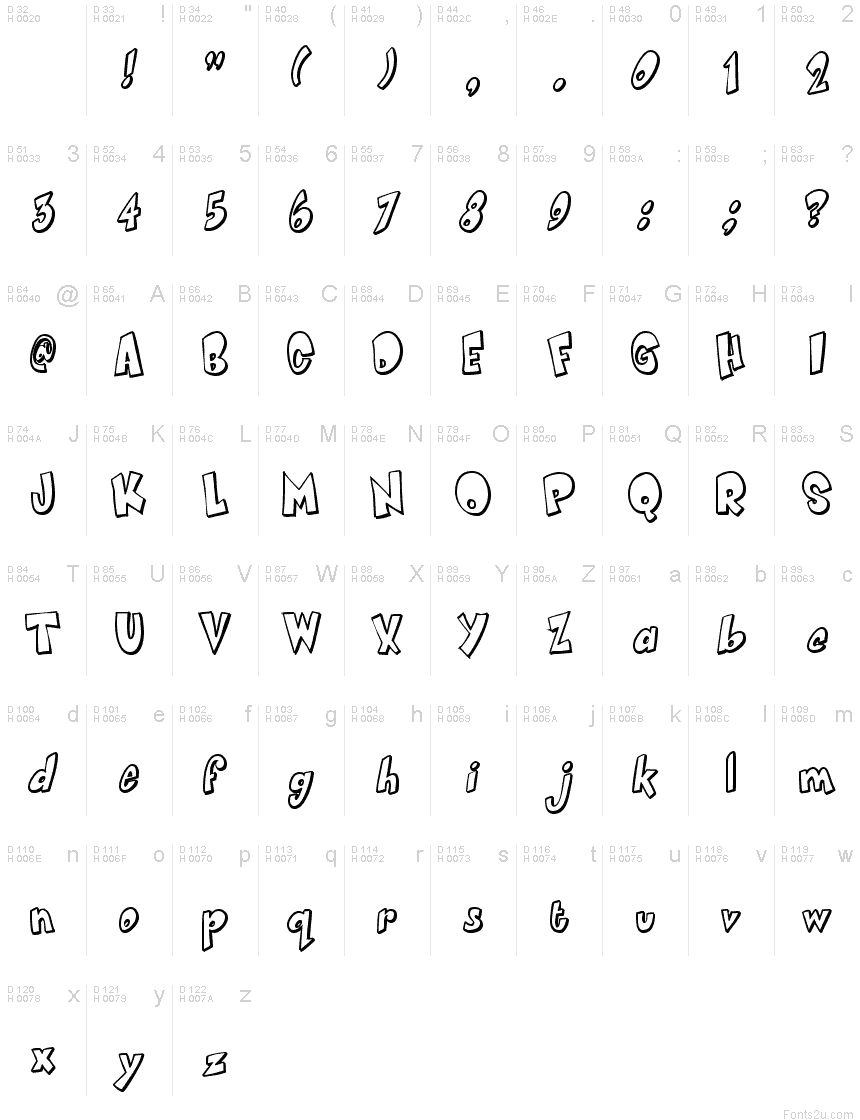
Smartie CAPS, od Font"a"licious Fonts, to darmowy komiksowy font display z pękatymi, bąbelkowymi literami i swobodnym, odręcznym charakterem. Grube kontury i lekko przechylone, obłe kształty nadają mu zabawny klimat kreskówek z lat 90., a nieregularny rytm sprawia, że całość nie wygląda zbyt gładko ani mechanicznie.
Idealnie pasuje do młodzieżowych marek, opakowań przekąsek, ulotek imprezowych, komiksowych nagłówków i wesołych banerów na strony www, gdzie darmowy krój pisma ma być luźny i nieformalny. Użyj go w krótkich tytułach, na okładkach lub tabliczkach, gdy chcesz, by same litery wnosiły radość, bo zaokrąglone kształty i lekko chwiejna linia same budują cały nastrój.